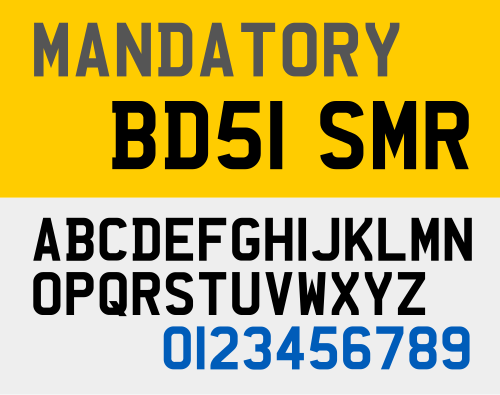
Mandatoryは、チャールズ・ライト書体[1]から開発された書体で、イギリスの車両登録プレートに採用された。ブロック体の文字と数字は、簡単に変更できないようにし、読みやすさを向上させるよう設計されており、MとWのストロークの分離は中央で尖っており、Qの末尾はより細くはっきりしている。イギリスで開発されたこの書体は、メルコスールのプレート採用前の2008年から2018年まで義務付けられていたブラジル、英連邦諸国、ヨルダン、イエメン(タイズ県)でも2018年から数字に使用されている。Mandatoryフォントは、K-Typeから個人使用のために無料でダウンロードできる。[2]
英国では、2001年9月1日以降に購入された車両登録プレートの文字には、必須の書体を使用し、幅、高さ、ストローク、間隔、余白に関する規定に準拠する必要があります。ナンバープレートの物理的特性は、英国規格BS AU 145e(2021年9月1日以前に装着されたプレートの場合はBS AU 145d)に規定されており、視認性、強度、反射率を規定しています。[3]